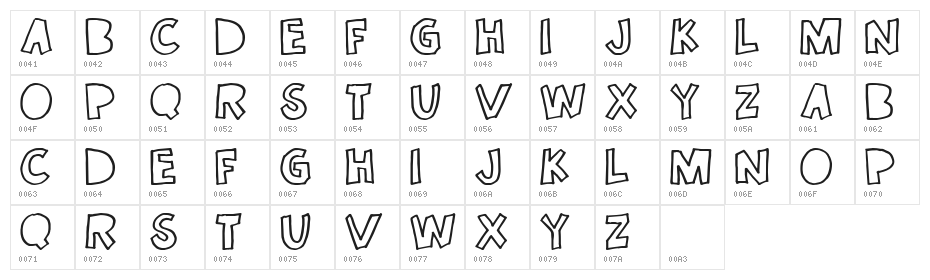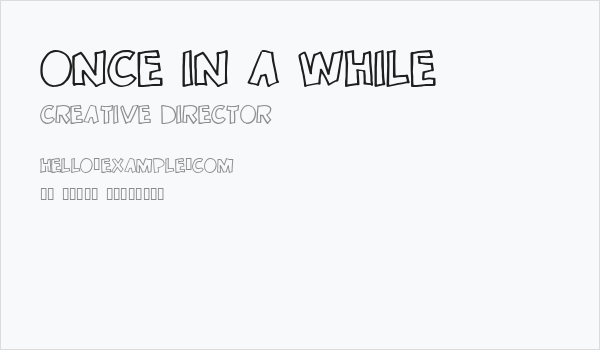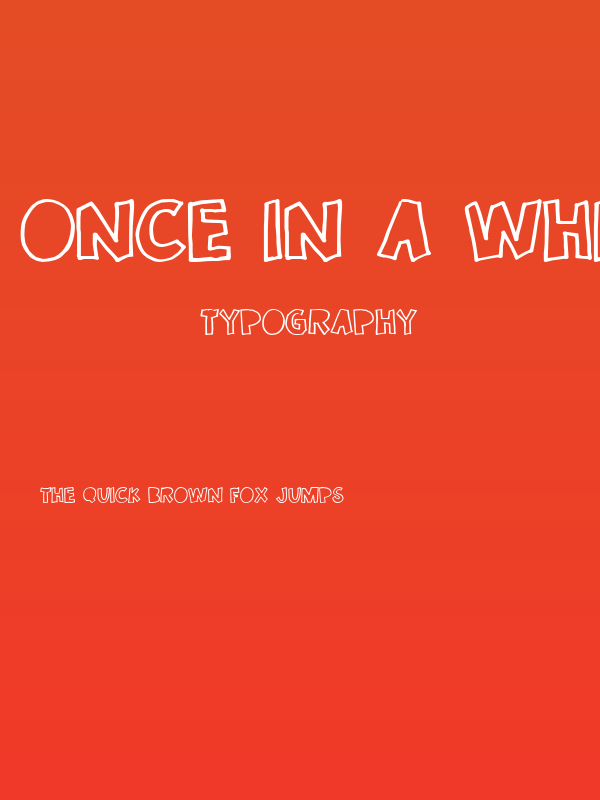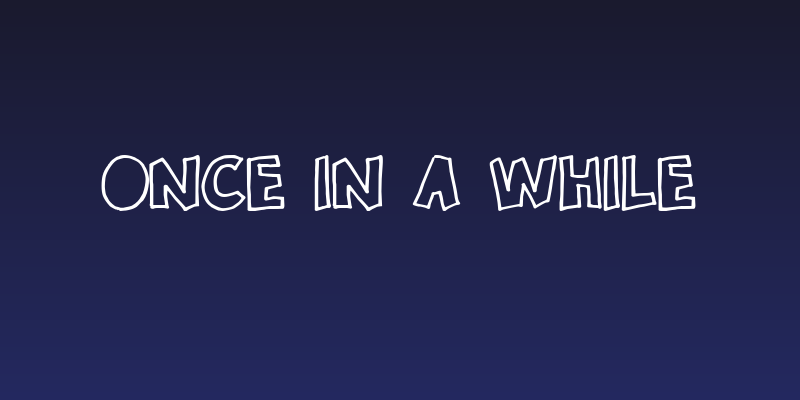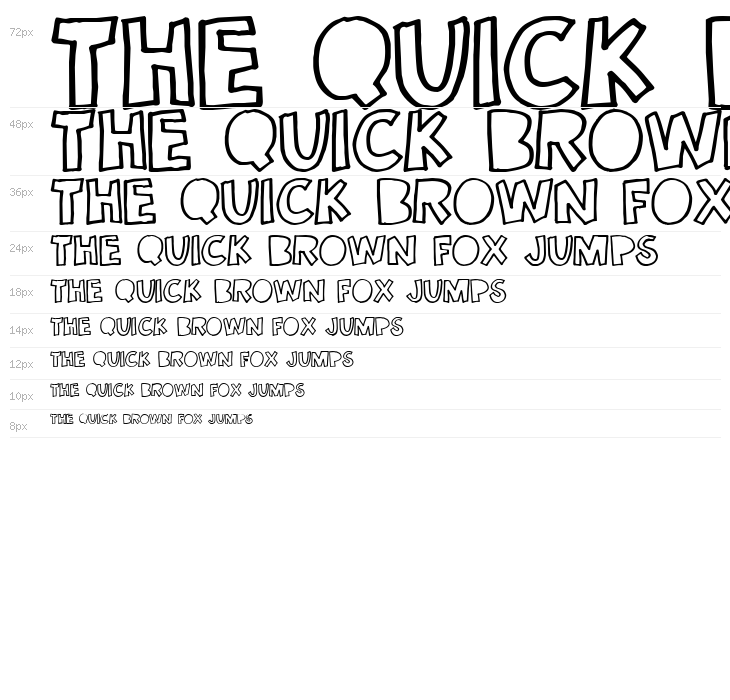
Once in a while Font
✎ Outline
| Categorie | Outline |
| Stile generale | Playful, Cartoonish |
| Progetti proposti | Ideal for children's books, comic strips, playful branding, and party invitations. |